娃娃体这种字体笔画类似于儿童书写字体的韵律,稚嫩青涩,线条弧度弹性大活泼可爱,其实娃娃体也是一种有法度有功夫的字体,是正经的书法。很多书法老师教孩子入门,会在楷书之前先教隶书,而隶书之前则先写娃娃体,手感熟了也别有风味。真正好字即使它是怪拙的却依然能够雅俗共赏。
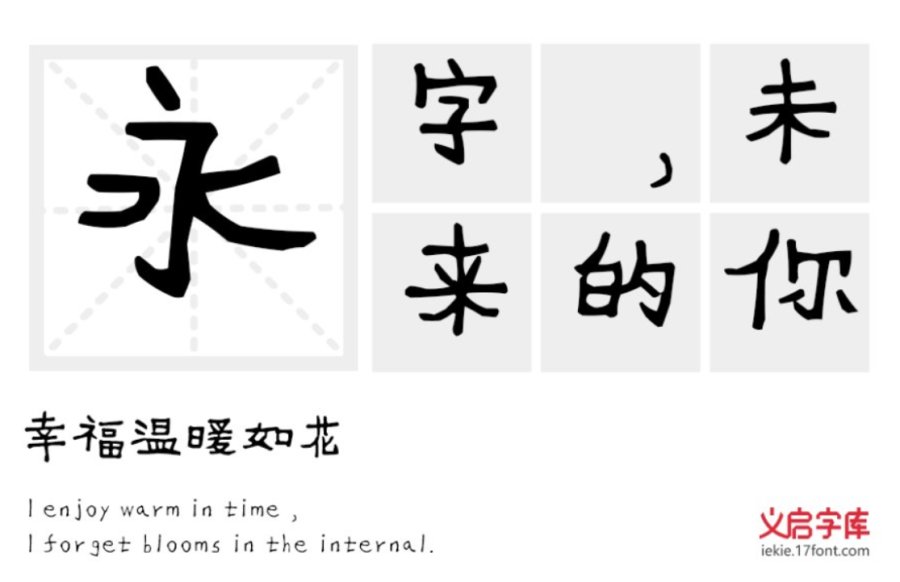
“义启童真体”这款字体简单不刻意,有种天然淳朴之美。还记得小时候的字是什么样的吗?义启童真体,带你体验儿时的天真与无邪。字形清晰有特色的易于看图找字。适用于游戏、综艺、儿童及母婴类品牌、logo、包装设计以及社交网络的个性化用字等领域。
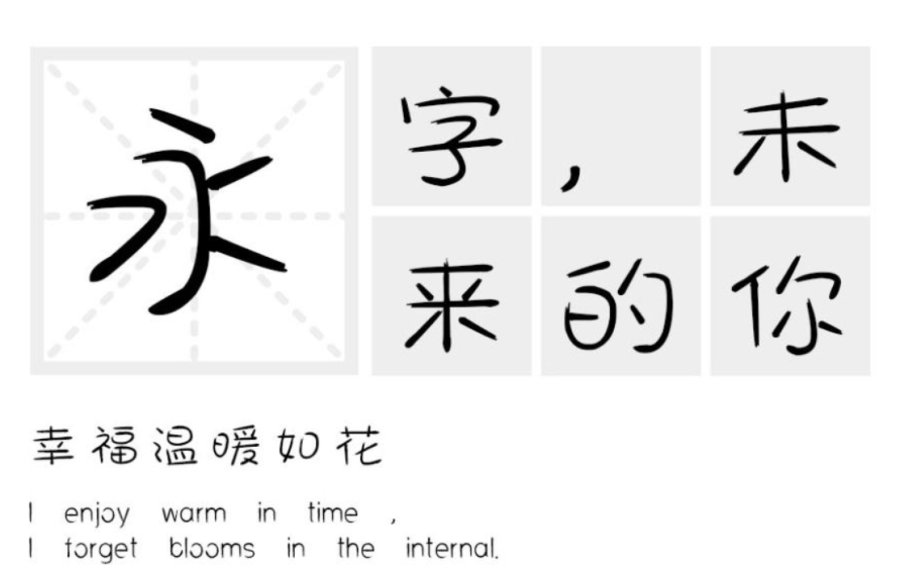
通常字形中的点、撇、捺、钩、提等笔画各具面目,而“汉标秃笔体”笔画运用了秃笔元素来构建,把这些笔画做成了秃笔,概括为飘逸的秃笔,并且使左右舒展的笔画尽量对称,最大限度地简化笔画秃笔造型。字形圆滑,青葱生趣。适用于儿童、女性用品品牌、包装、logo设计、广告、印刷、屏显等领域。
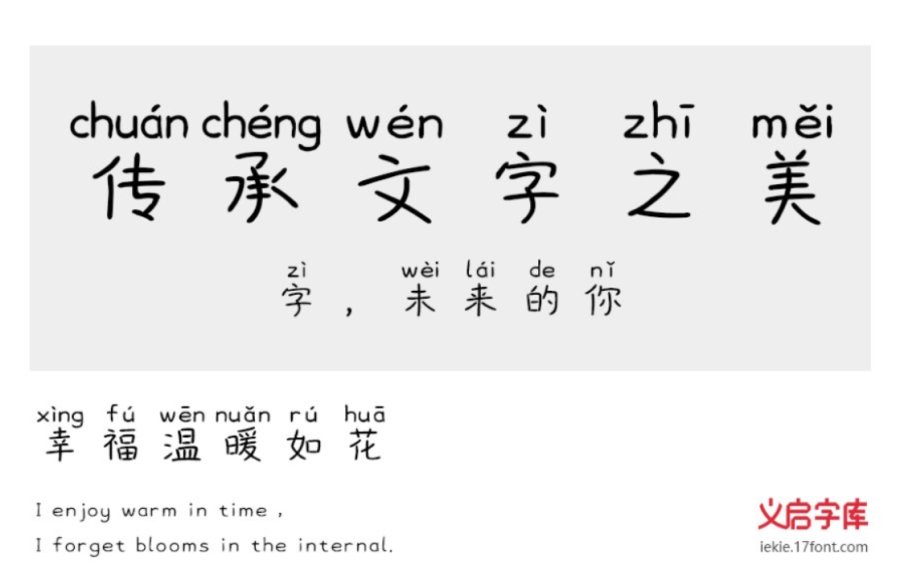
“小宝贝儿拼音体”是一款带拼音的字体,富有意趣的笔画,生动多变的结构,可爱的气质拿捏的恰到好处。适用于少儿类书刊,及现代诗歌、短文的排版以及文化、商业类品牌的广告语设计。